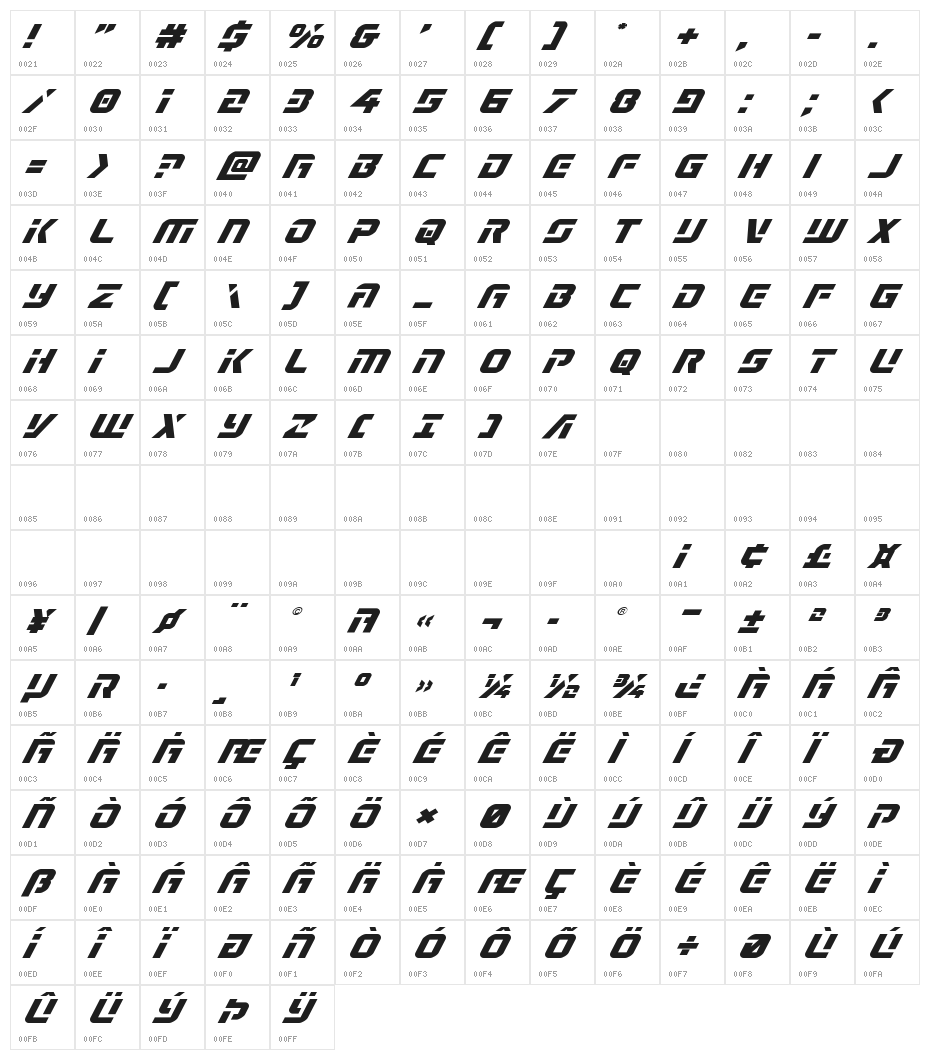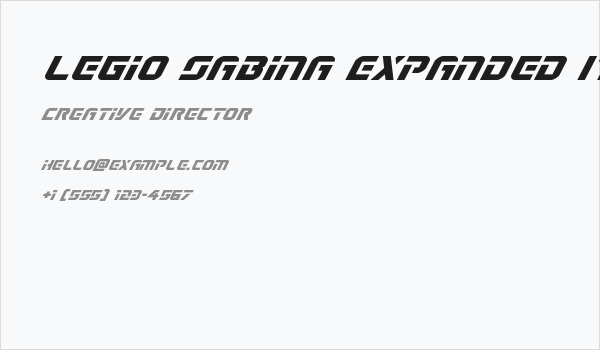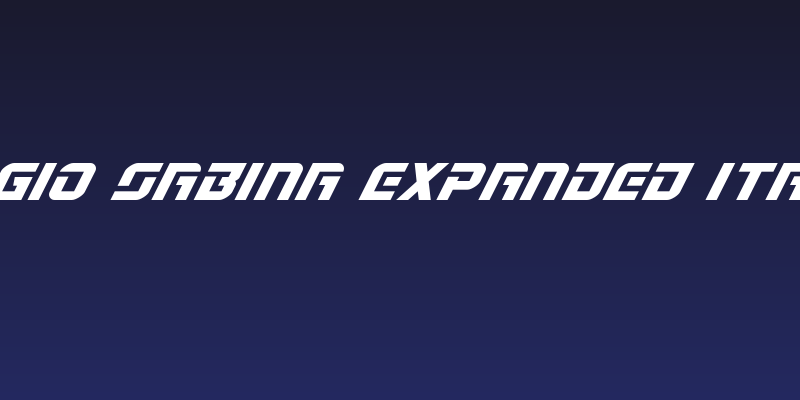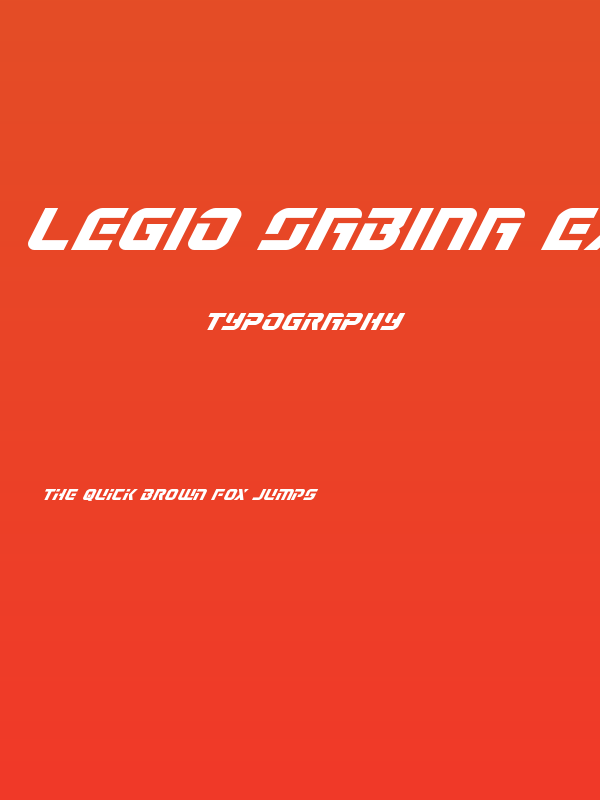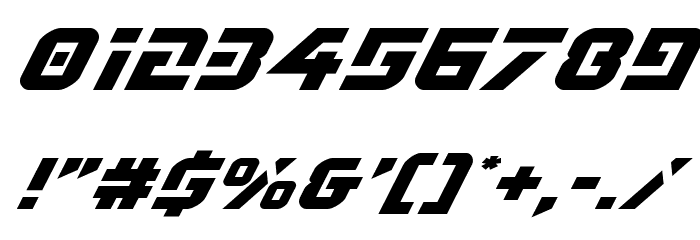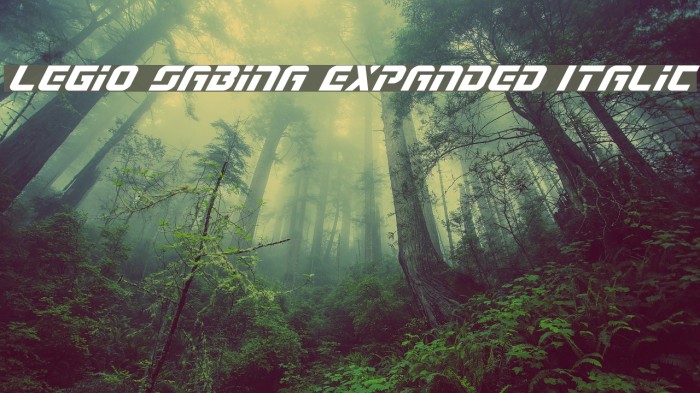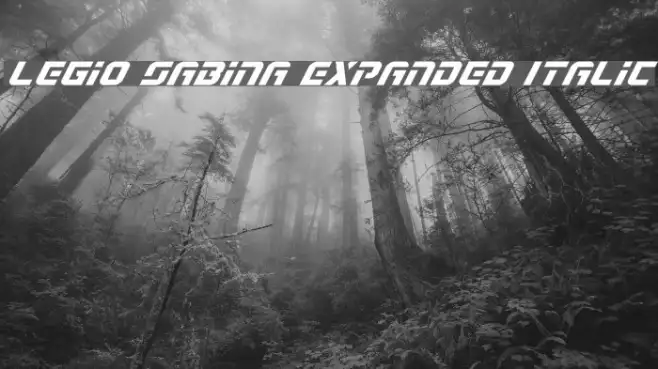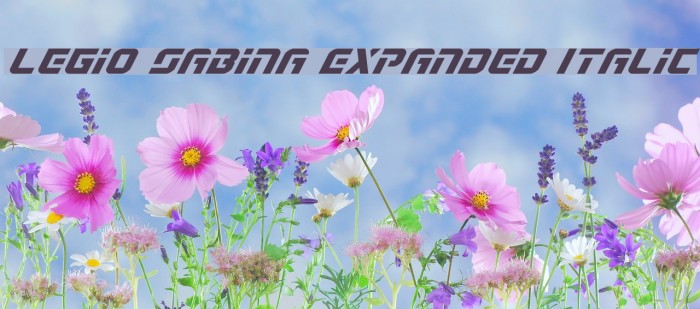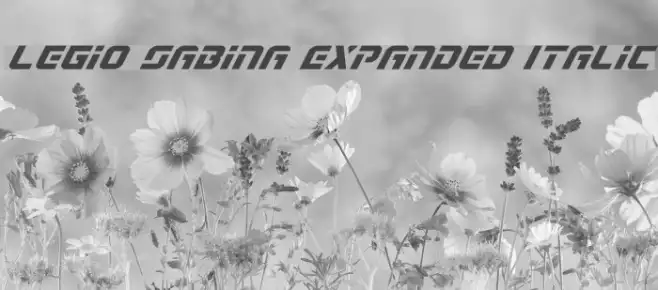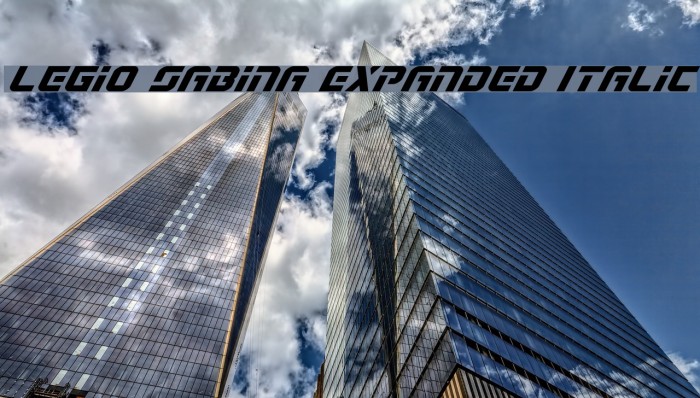
Legio Sabina Expanded Italic Font
| Proyectos propuestos | Ideal for sports branding, futuristic designs, technology-related projects, and dynamic advertising campaigns. |